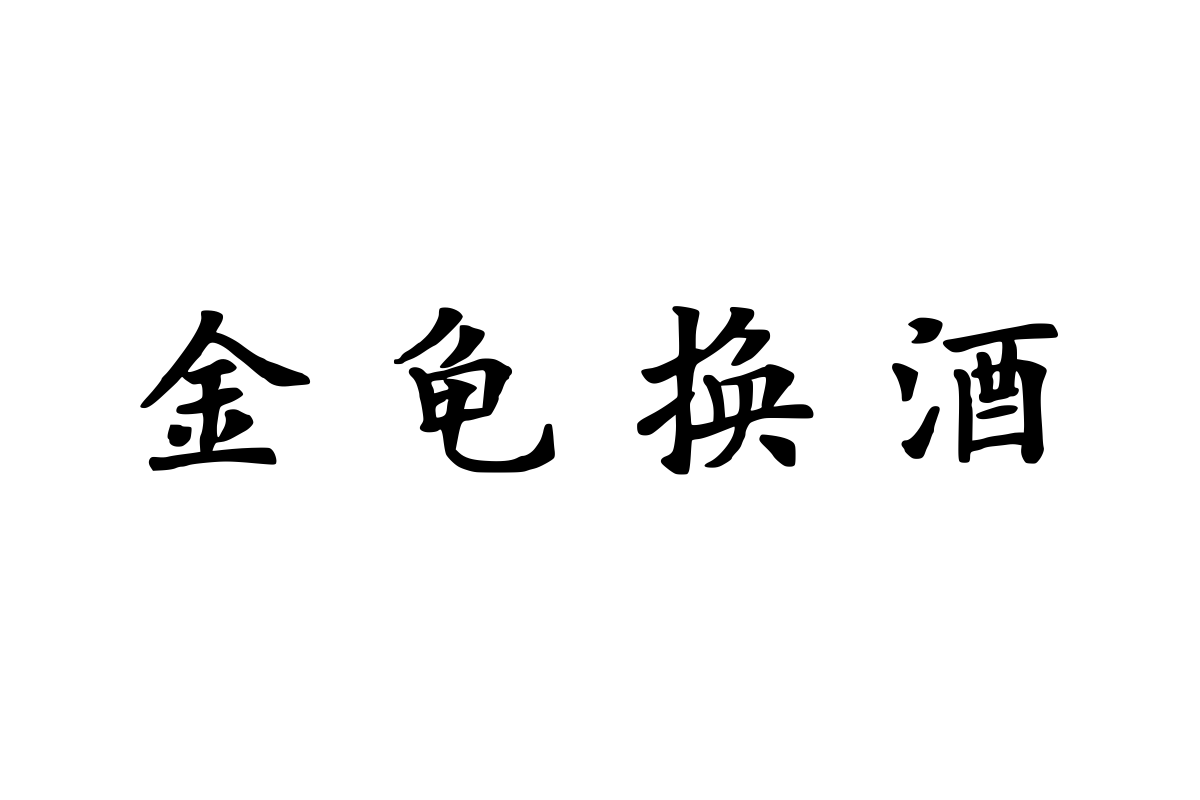
兰米标准楷体加粗是一款具有独特特色的中文字体,它结合了现代与古典的元素,创造出一种既优雅又有力的视觉体验。该字体的笔画粗细适中,线条流畅而有力,给人一种清晰、易读的感觉。
兰米标准楷体加粗的特点在于其独特的加粗效果。这种加粗方式使得字体看起来更加醒目,能够吸引读者的注意力。同时,由于加粗的线条较粗,因此也使得字体在视觉上显得更加稳重和权威。
此外,兰米标准楷体加粗还注重细节的处理。它的每个笔画都经过精心设计,使得整个字体看起来既整齐又富有变化。这使得兰米标准楷体加粗不仅适合正式的文件和报告,也适合用于各种创意设计,如海报、广告、网站等。
总的来说,兰米标准楷体加粗是一款非常实用的字体,无论是在商业还是个人项目中,它都能提供出色的视觉效果和阅读体验。